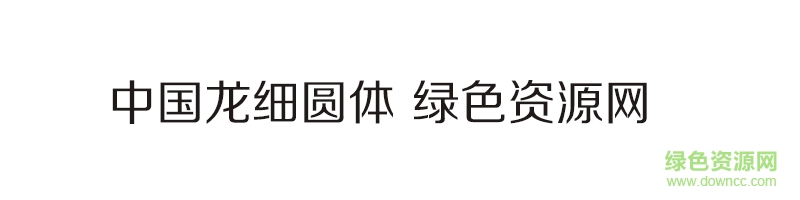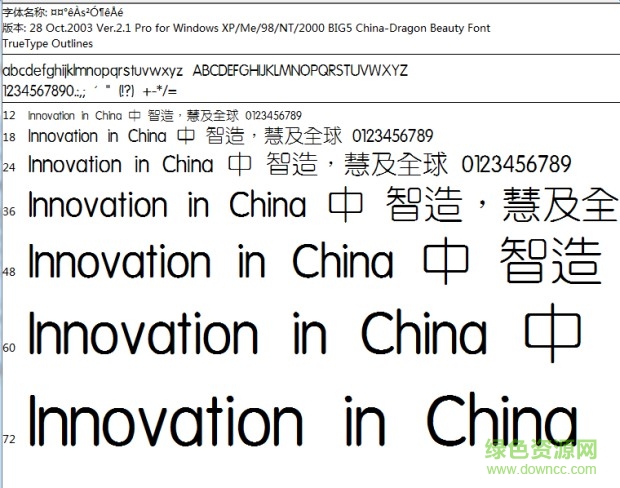
中國龍細(xì)圓體字體是一款中國龍字體庫的細(xì)圓字體,此款字體字型結(jié)構(gòu)簡單,適用于中文和英文,字體超炫非常適合于美工設(shè)計(jì)。有喜歡的朋友可以來綠色資源網(wǎng)下載使用!
中國龍細(xì)圓體是應(yīng)用于設(shè)計(jì)方面的中文簡體漢字,該字體字體端正簡潔,整體效果十分出色,非常適合顯示應(yīng)用與閱讀。